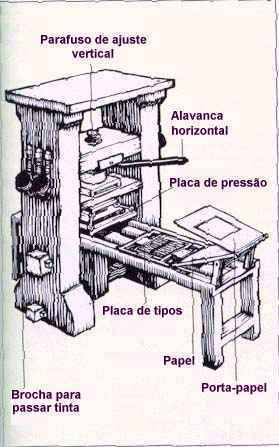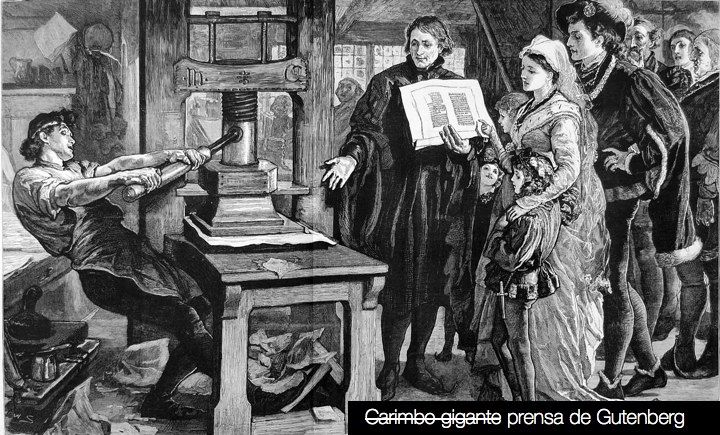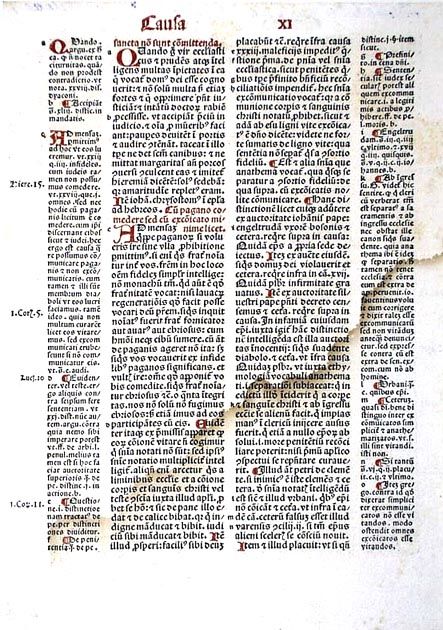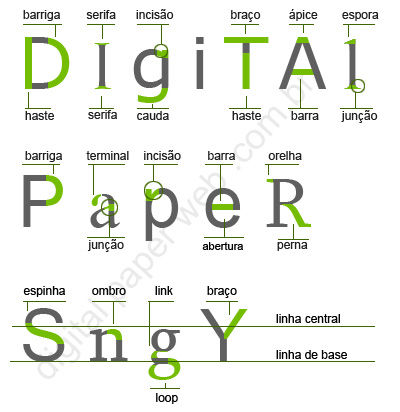
TIPOGRAFIA
1. Nascimento
1. Surgiu na Europa em 1440, com a prensa de tipos móveis de João Gutenberg.
1. Gutenberg criou letras que podiam ser encaixadas em uma placa, formando o texto.
1. Pegava-se esta placa, aplicava-se tinta, colocava-se o papel sobre a placa e passava-se, com pressão, a prensa por cima para carimbar.
1. Apenas cinquenta anos após o feito de Gutenberg, 13 milhões de livros circulavam em uma Europa de 100 milhões de habitantes.
2. Evolução
1. Variação de tamanhos e tipos de letra.
1. Os profissionais se adaptaram a ler e escrever com os tipos invertidos, característica da tipografia ao montar as placas.
1. As prensas, que eram manuais, foram substituídas por máquinas semi-automáticas e automáticas, assim como a alimentação do papel.
1. A velocidade das folhas passou a ser de 30 por minuto.
2. A arte de compor e imprimir com tipos.
1. Principais Características
1. A tipografia influencia o caráter e a qualidade de um projeto. Ela pode produzir diferentes efeitos no leitor, simbolizar movimentos artísticos, políticos ou filosóficos, ou ainda expressar personalidade.
1. As fontes tipográficas variam de estilo. As mais atraentes e que chamam a atenção são utilizadas em manchetes e propagandas.